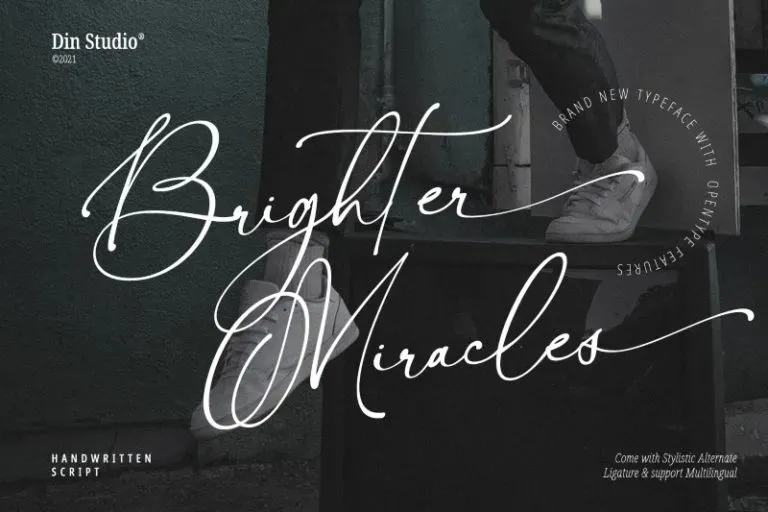
Esta é uma fonte Signature com um toque moderno e sofisticado, feita pelo designer Din Studio. É projetada para trazer vida a sua marca e adicionar elegância, modernidade e estilo. Excelente para projetos de branding nas redes sociais, criação de moda, citações impressas, embalagens ou até mesmo como um overlay estiloso ao texto sobre qualquer imagem de fundo. “Brighter Miracles Font” é uma fonte feita à mão especializada em destacar sua marca e dar novo vida a suas criações. Não perca tempo – ele vai revolucionar a maneira que você compõe textos.